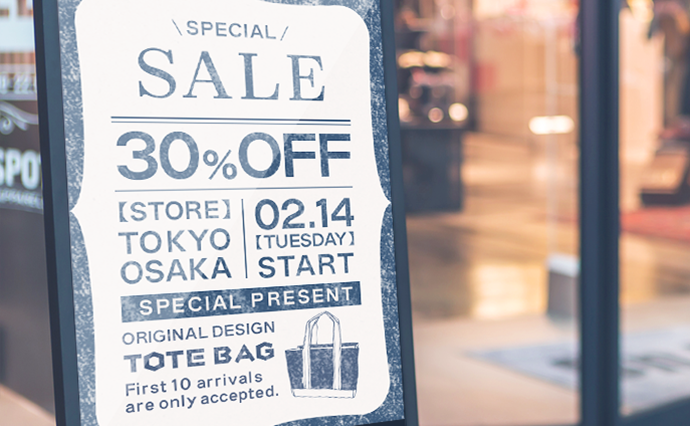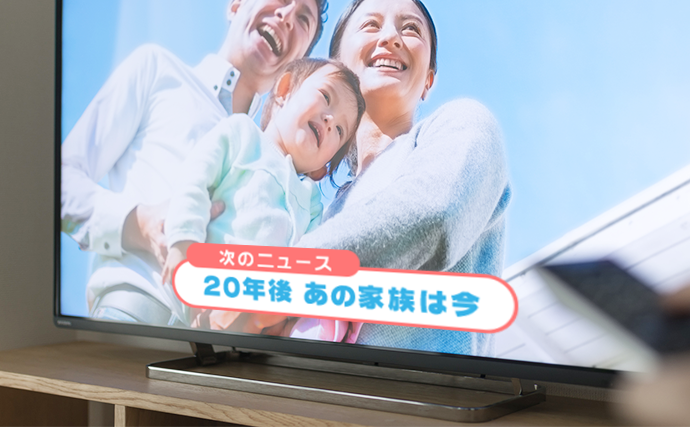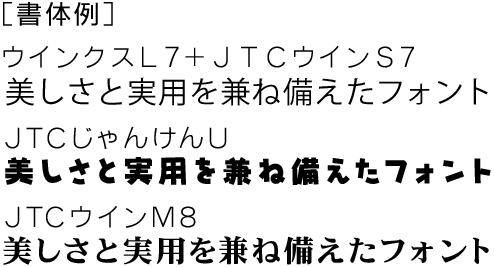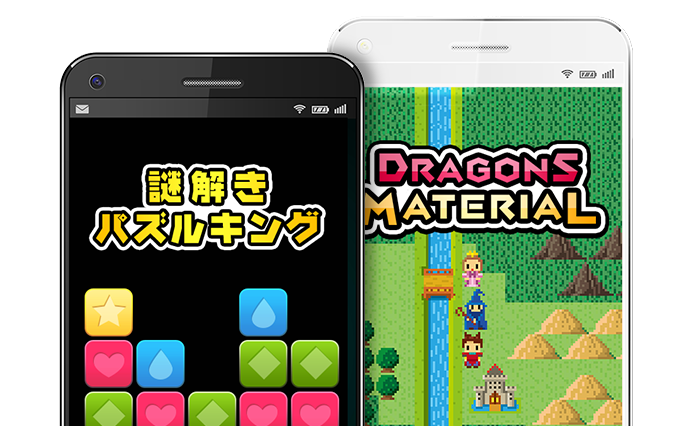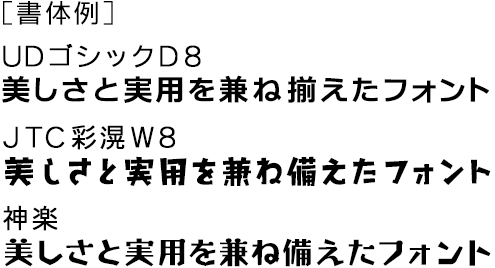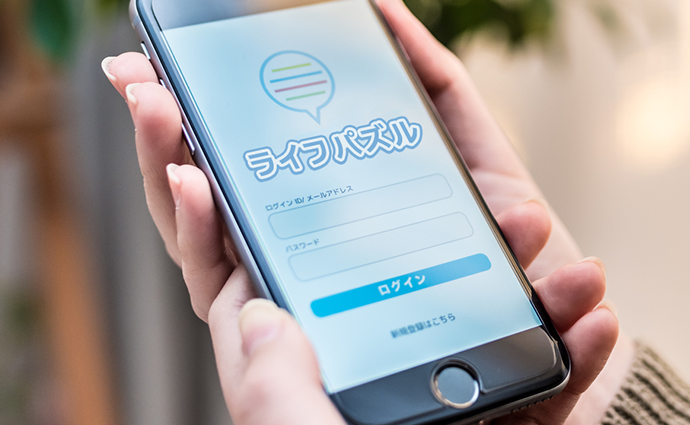
NIS Fontは、スーパーマーケットのPOPやTV番組のテロップ、ホームページ制作など幅広くご利用いただいております。
ここでは、そんなモデルケースの一例をご紹介します。
POP
書体ひとつで印象・売上が大きく変動するPOP。NIS Fontでは、インパクト・キャッチーさを重視したPOP向けフォントを豊富にご用意。スーパーマーケットをはじめ、大型ショッピングセンターなど、消費者の方たちが日頃から訪れる機会の多いシーンで幅広く採用いただいています。
インパクト・キャッチーさを
重視した書体
を多数ご用意
幅広くご利用いただいている豊富な実績
消費者が日頃目にしている
安定感
テロップ
わずかな時間でもすぐに理解してもらえるよう、可読性に優れたフォントを多数ご用意。明朝体からPOP体まで、視聴者が1度は目にしている書体を幅広く取りそろえています。ニュース番組や報道番組をはじめ、昨今では欠かせないバラエティテロップなど幅広く採用いただいています。
番組特性に合わせた
フォント
可読性・伝達性を徹底追求
消費者が日頃目にしている
安定感
ゲーム・アプリ
ゲームやアプリの世界観を表現するためにフォントは重要なファクター。可読性以上に、インパクトや印象に残る書体が好まれるため、POP書体が充実しているNIS Fontは最適です。ゲームタイトルはもちろん、ゲーム内テロップでも世界観にマッチした書体として某有名ゲームにも採用いただいています。数文字〜数十文字の文字デザインをフォント化したオリジナルフォント作成もおすすめです。
ゲームの世界観にふさわしいPOP書体が充実
某有名ゲームにも採用される豊富な実績
オリジナルフォントの作成も可能